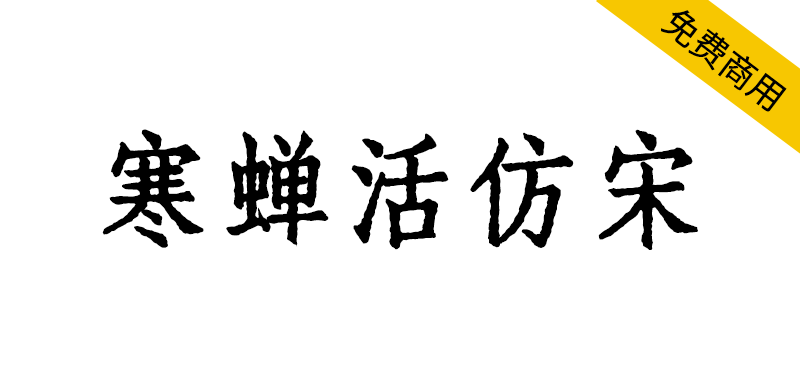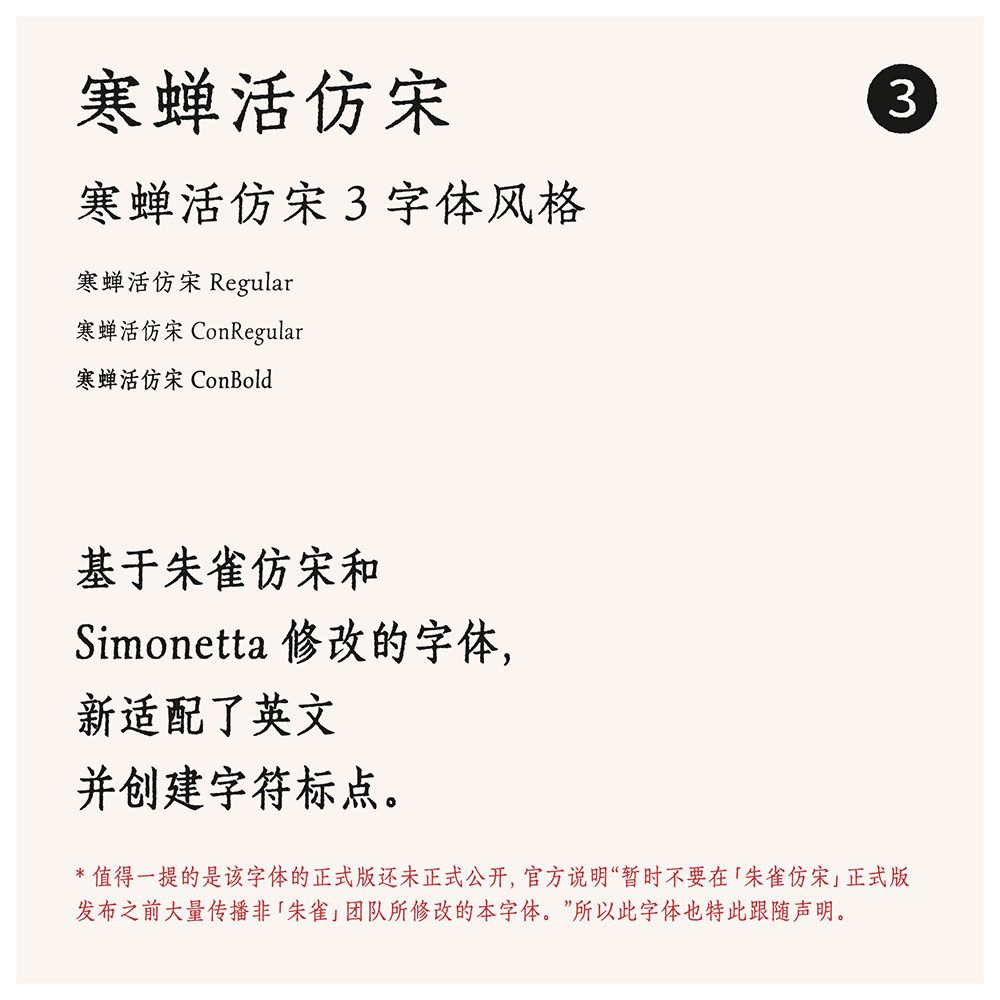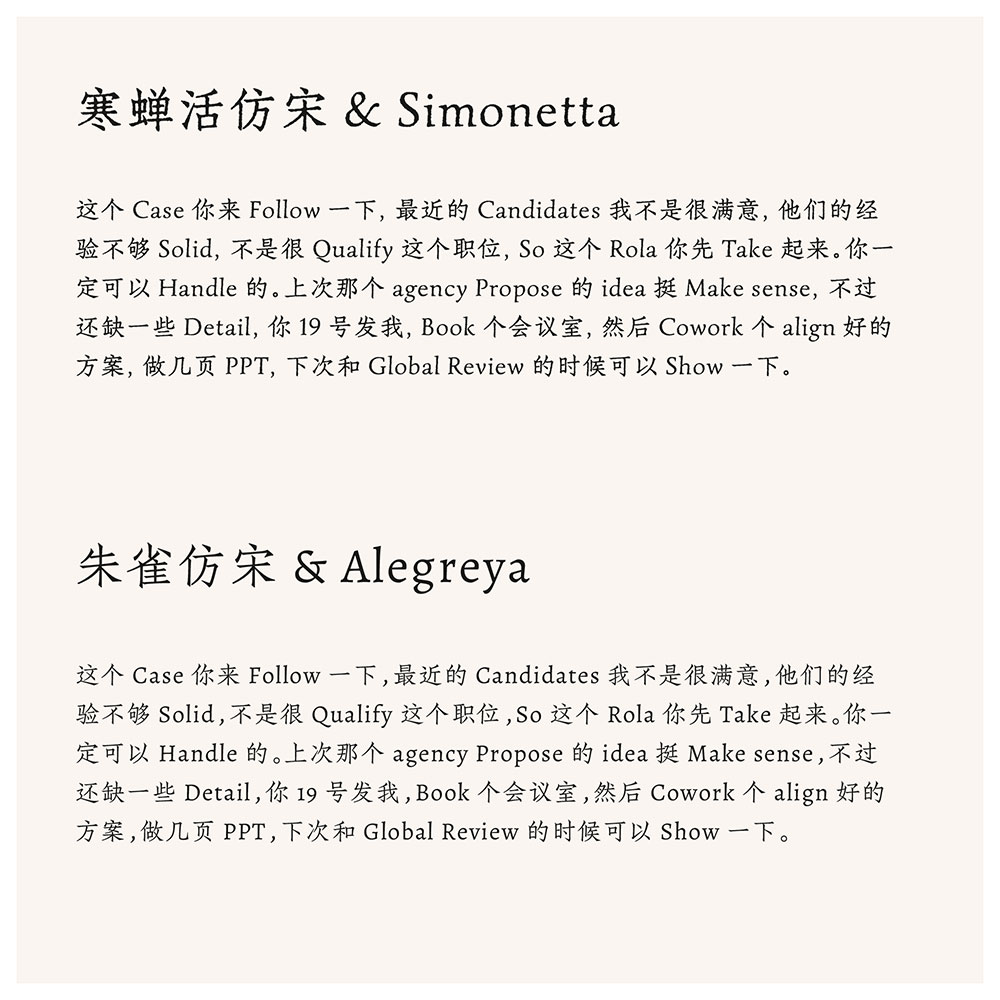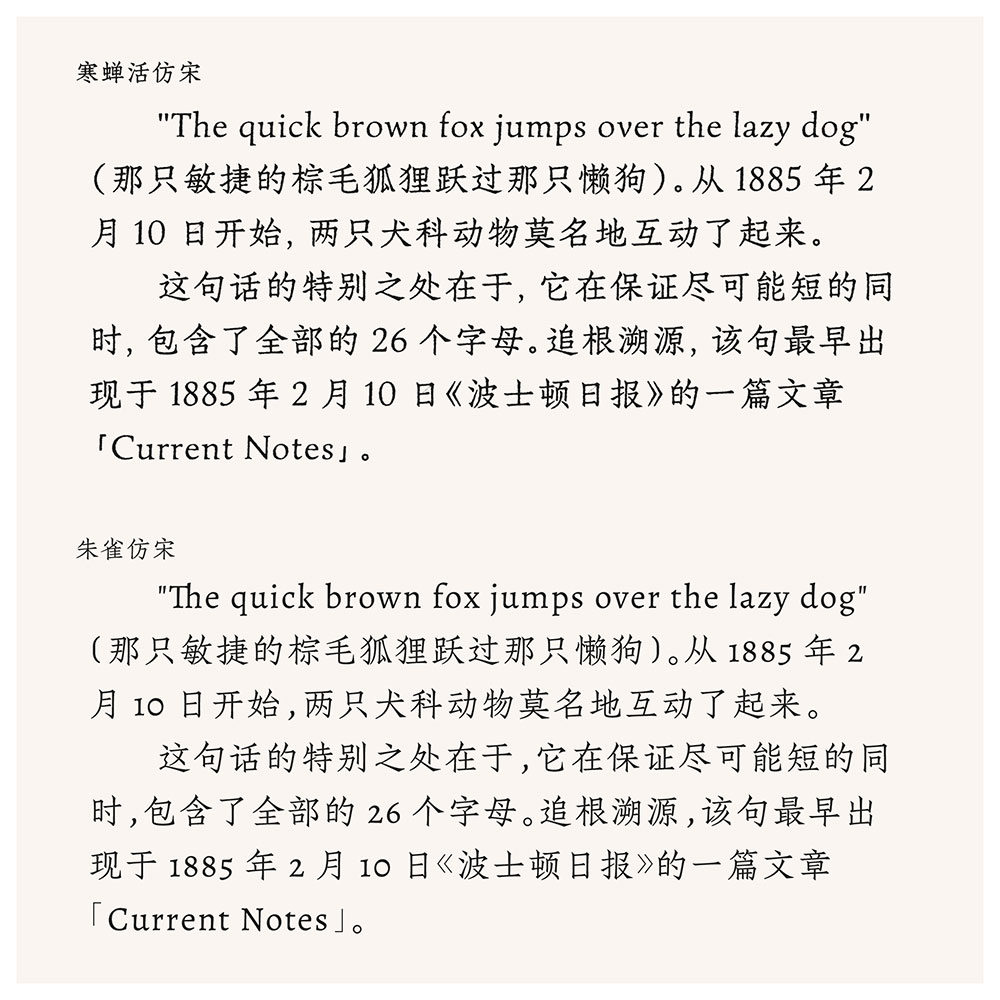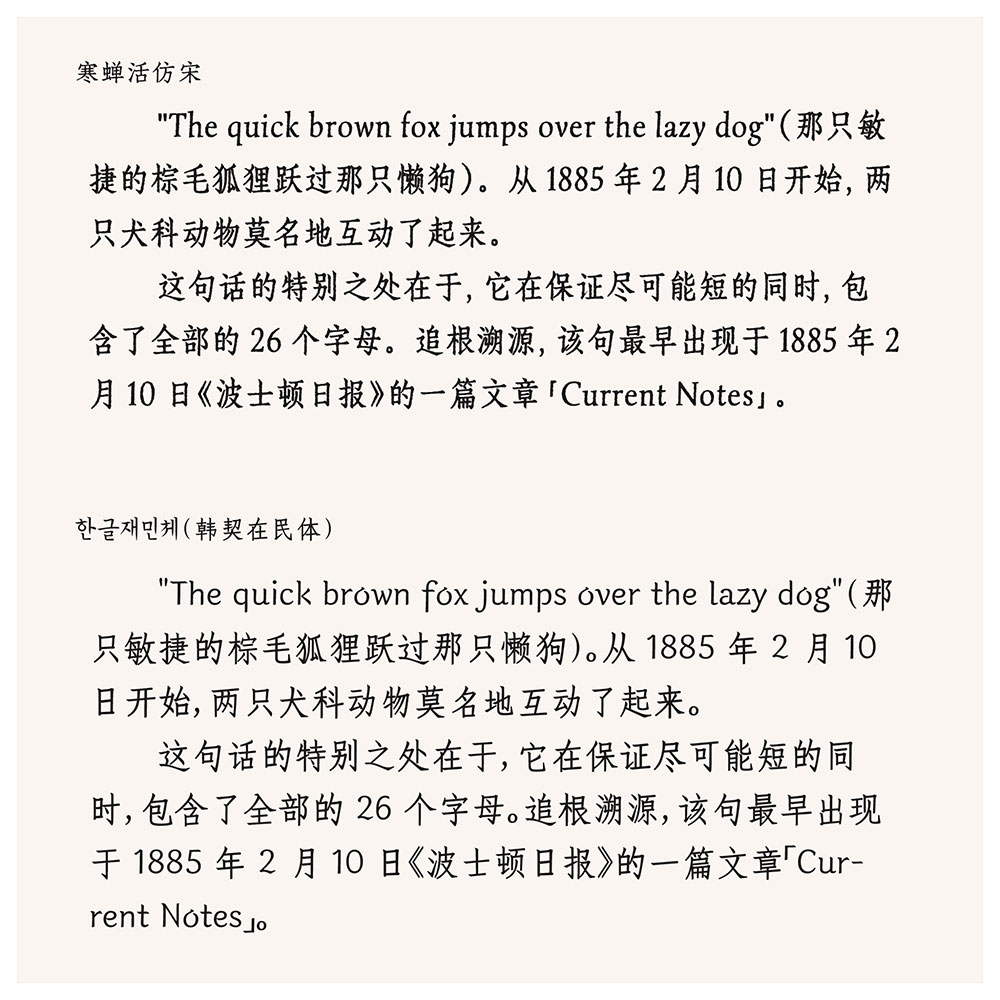
寒蝉活仿宋是一个活字印刷字体项目,模拟印刷时的轻度油墨溢出,基于朱雀仿宋和Simonetta修改的字体,新适配了英文并创建字符标点。
本项目旨在已有的开源字体上修改模拟具有轻度油墨溢出的效果。此为新的尝试,使用较为复古的字形字体,不太适用于较正式的场合。本系列属于反向造字,将清晰的字体变得模糊,将顺滑流畅的曲线修改为驳杂的曲线。
字体主要模拟了油墨印刷的真实感,这和软件使用字体生成的效果有一些差异,所以字体文件还是有必要的。驳杂的曲线会导致大量的节点,字体文件势必会变大。所以对字符数量做一些删减,优先保留网络常用简繁字符。
值得注意的是和真实的印刷再扫描字体有较大差距。折中取轻度的斑驳效果,与原字体对比却又多了几分真实。或许对少量海报设计项目和新媒体有些许用处。